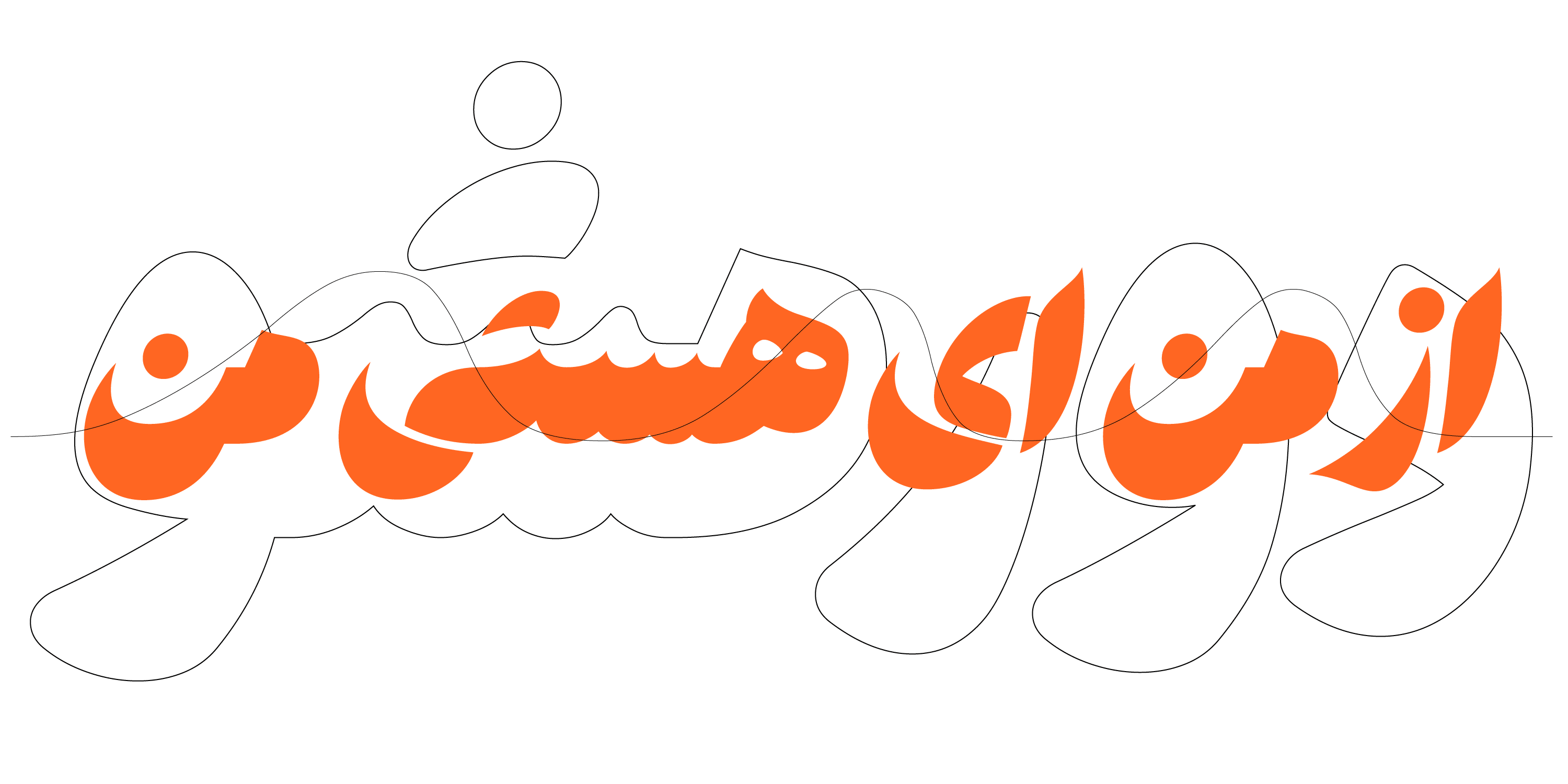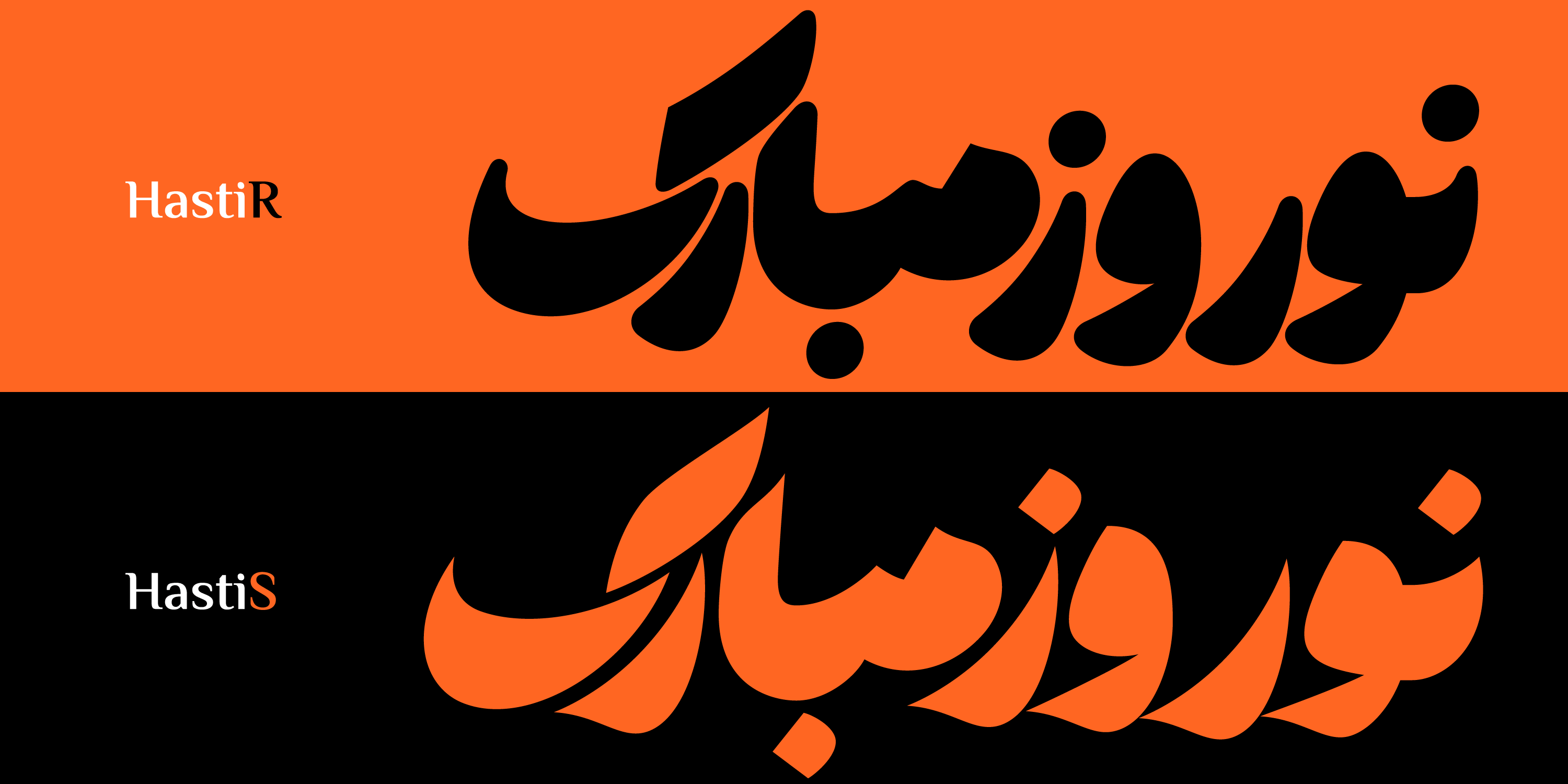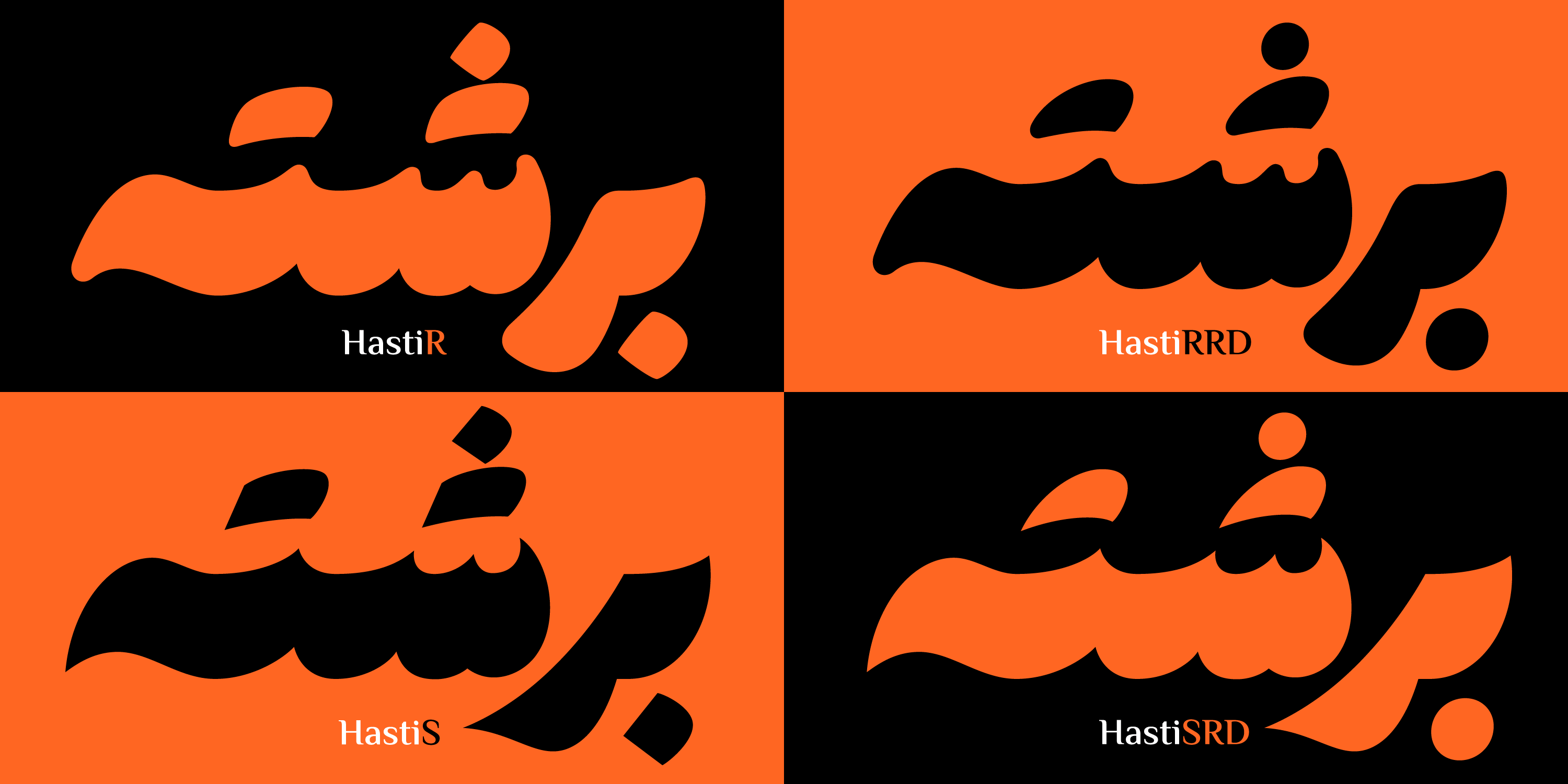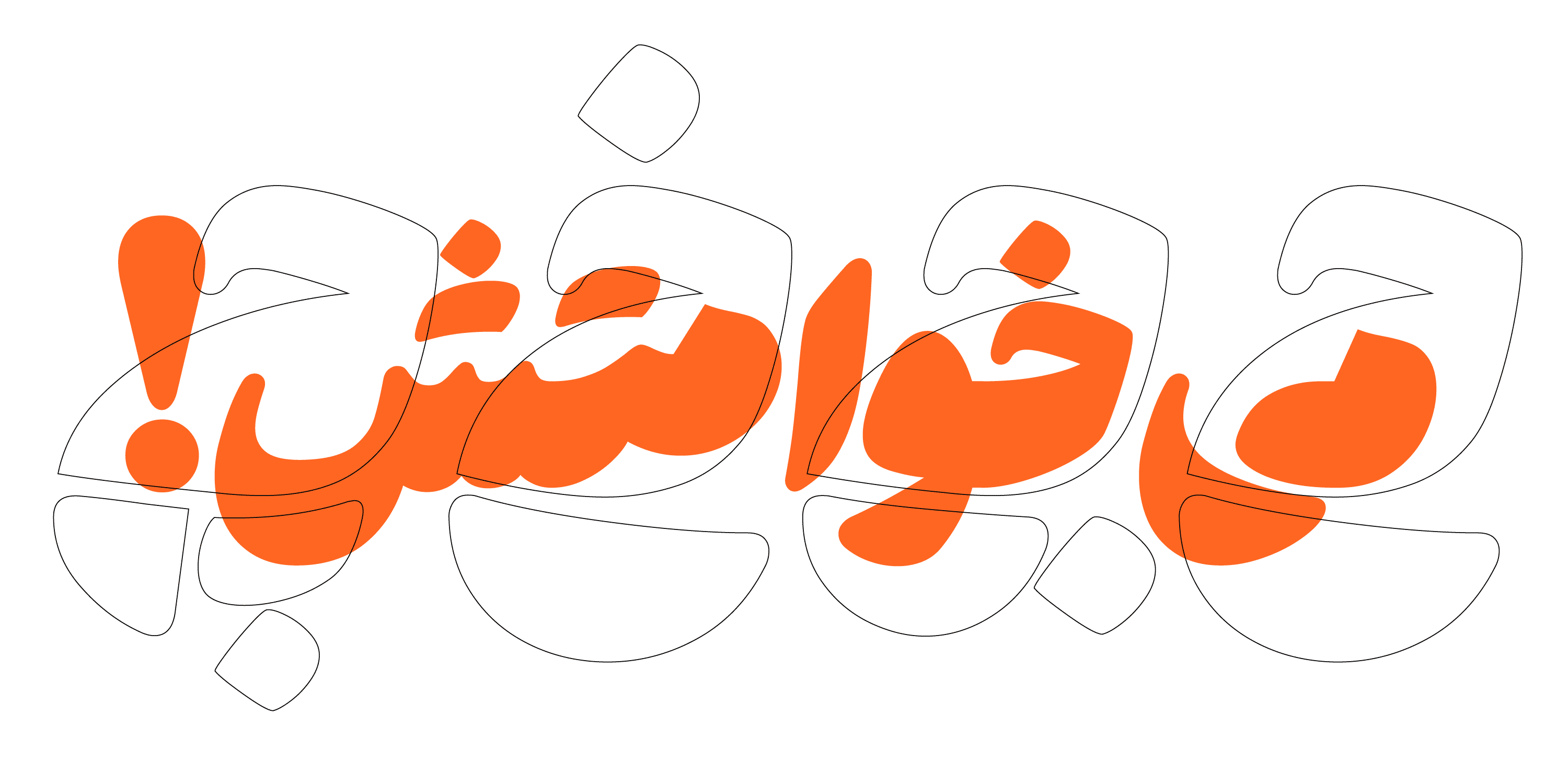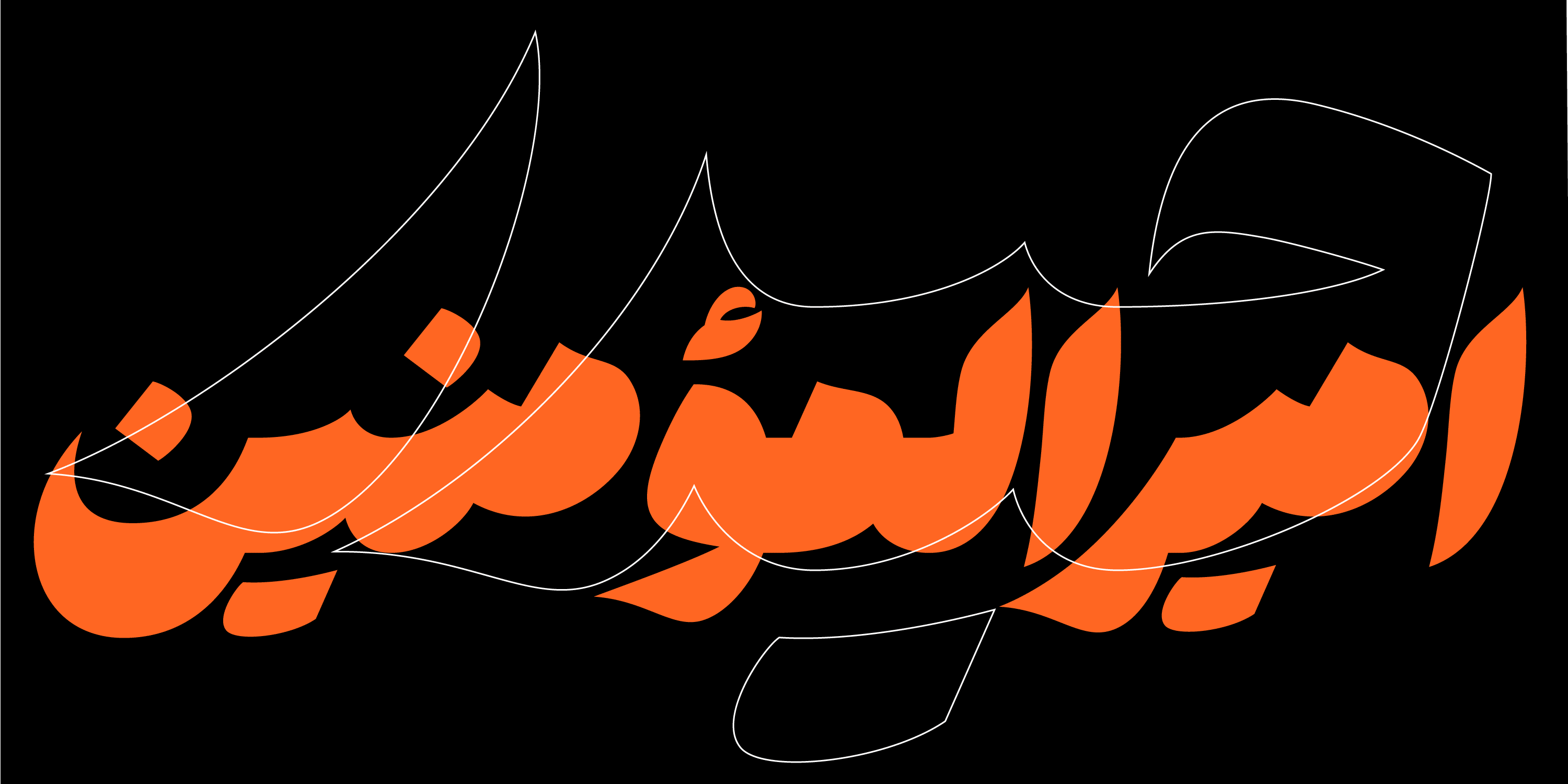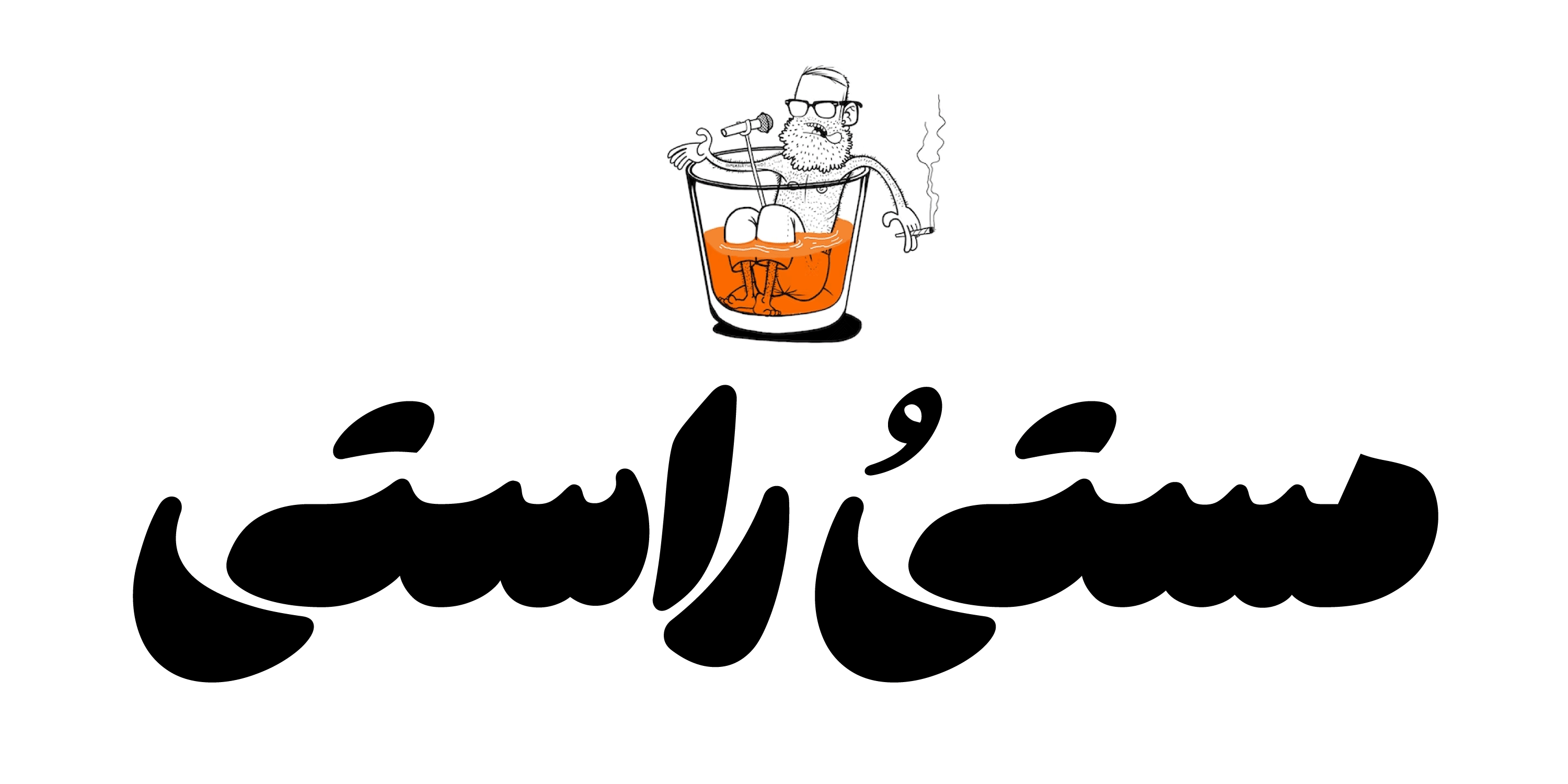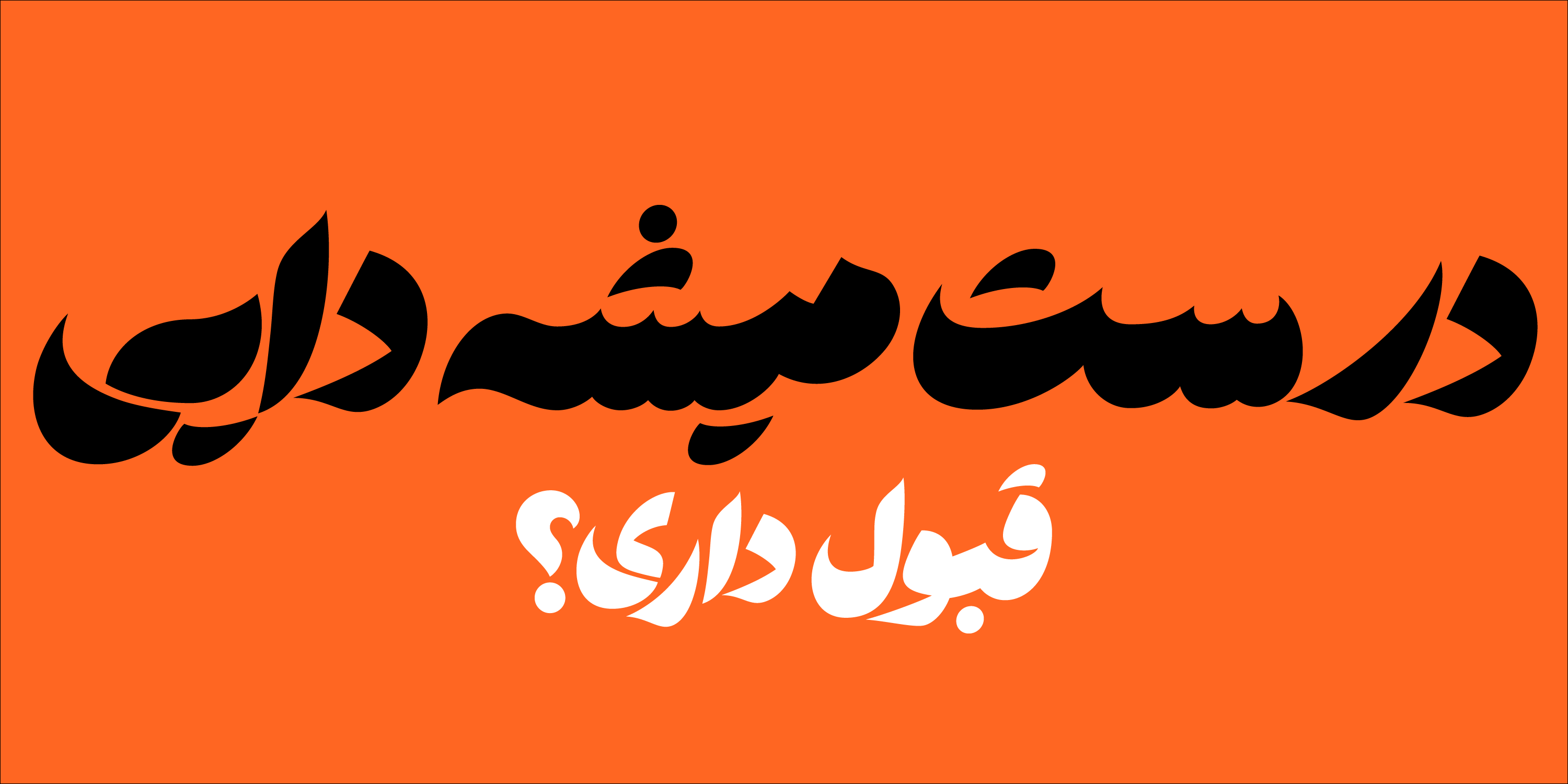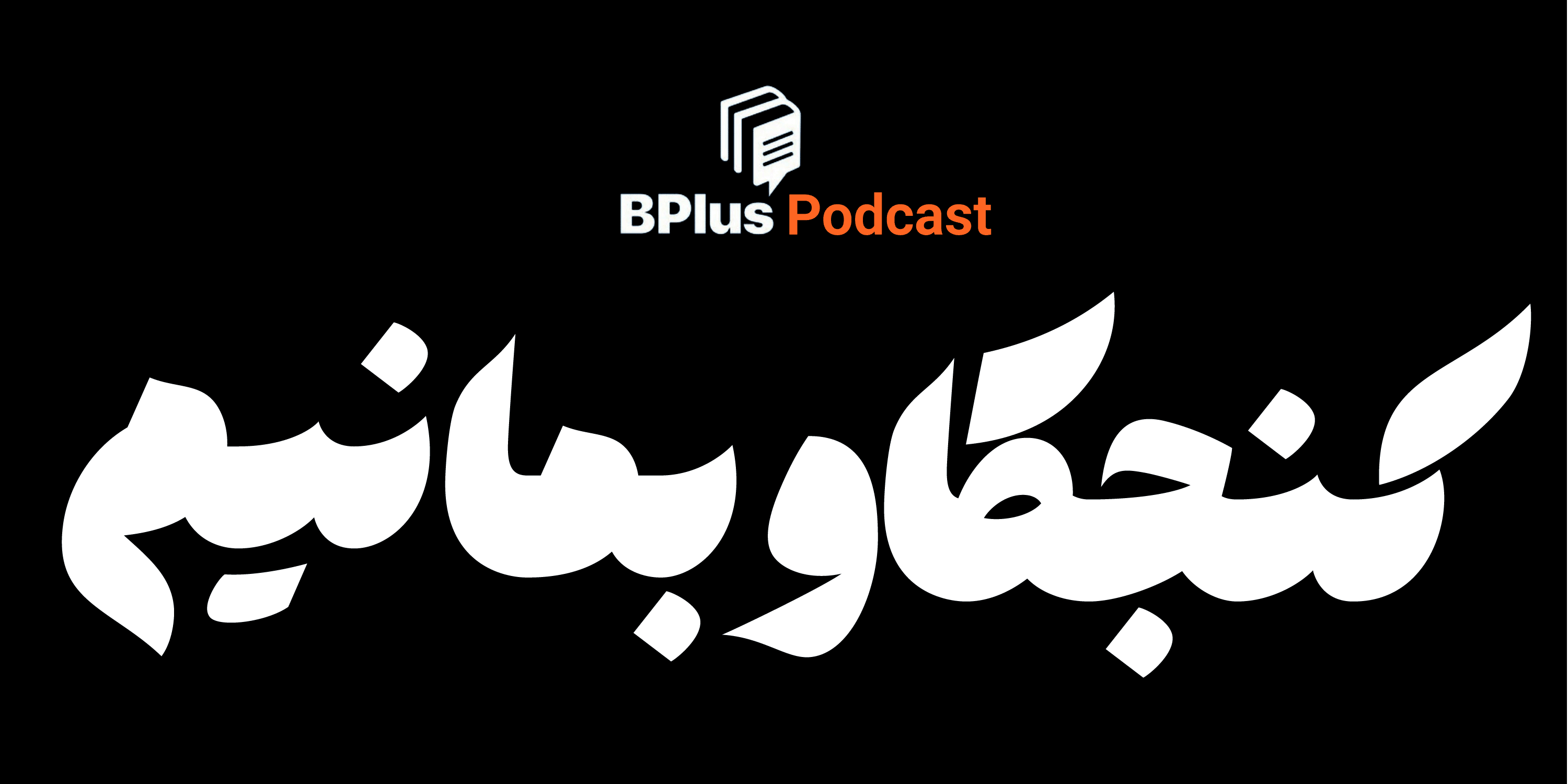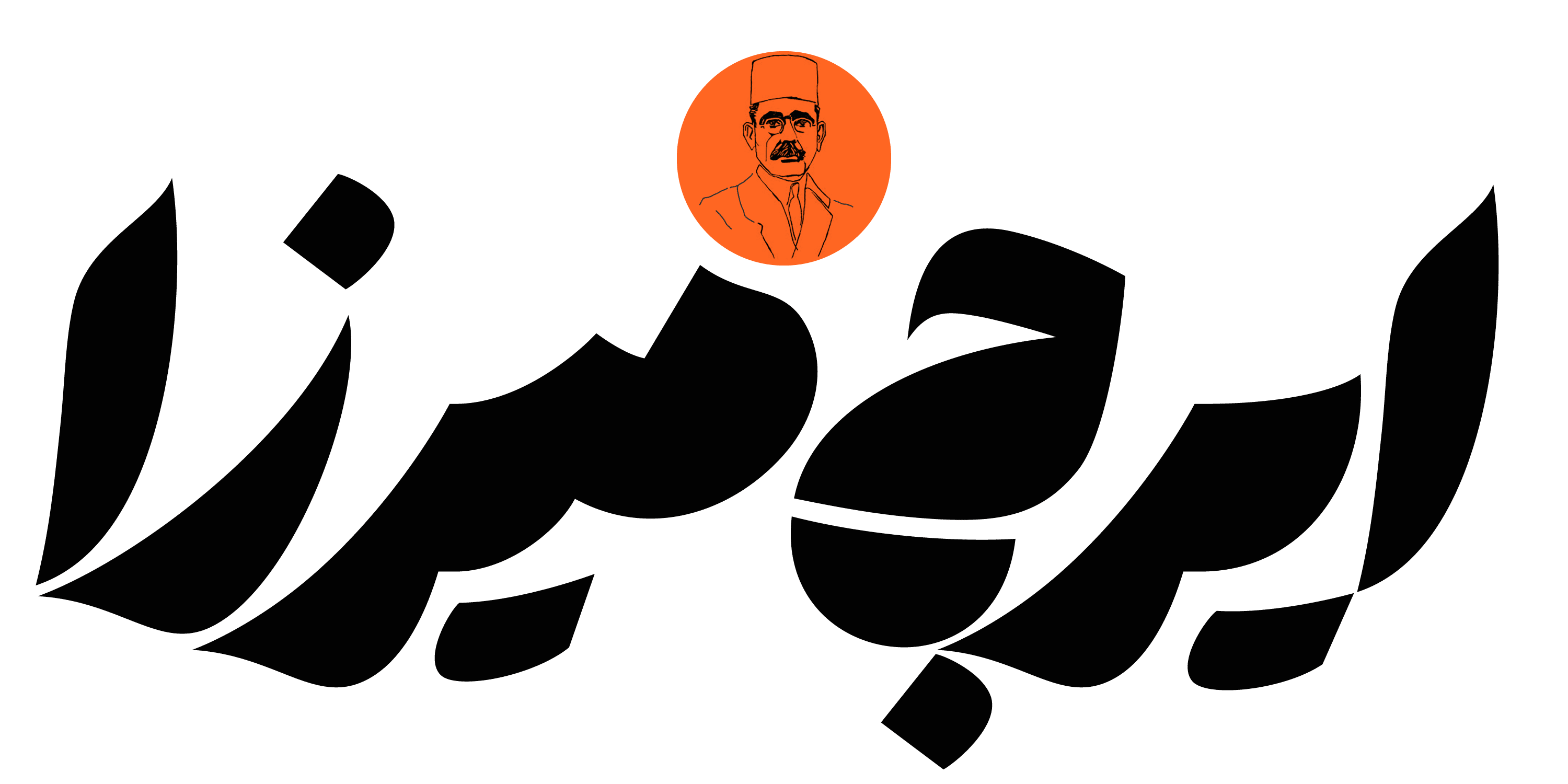
طی نیم قرن گذشته با ظهور دستگاه چاپ و کامپیوتر، خط فارسی کاملا پیرو خط نسخ بوده است اما نستعلیق هنوز برای ما دوست داشتنی و آشناست. هنوز شعر فارسی را جز با نستعلیق نمیتوانیم بپذیریم و اگر بخواهیم حس و حال ایرانی را در نوشتهای نشان دهیم نستعلیق را انتخاب میکنیم. فونت هستی انعکاسی از این حس آشنا و دوست داشتنی، در قالب یک فونت معاصر است.
فونت هستی متاثر از نستعلیقِ بازاری است. دیوار نویسیها و تبلیغات شهری که با قلمهای درشت خطاطی میشوند، ظرافت نستعلیق هنری را ندارد این حروف معمولاً بولدتر و فشردهتر نوشته میشود. فونت هستی تحت تاثیر این نوع حروف، حجیم و فشرده طراحی شده است.
در فونت هستی اثری از ترکیبات و اتصالات نستعلیق نیست اما شکل حروف تا حد امکان شبیه نستعلیق است.
برای فشردگی بیشتر، فرم حروف "ک ی ح" شکسته و منقطع شده است.
نسخه جدید فونت هستی دارای دو سبک گرد Rounded و تیز Sharp است.
هرکدام از دو سبک گرد و تیز با دو سبک نقطه در بسته وجود دارد. (نقطه کلاسیک و نقطه گرد)
فونت هستی در سیزدهمین رقابت جهانی گرانشان (۲۰۲۴) در بخش فونتهای عربی جایزه دوم را کسب کرد. (داوران این دوره با سختگیری جایزه نخست را به هیچ اثری اهدا نکردند.)
جایگزینهای خودکار
در هستی با توجه به حرف قبل یا بعد حروف کشیدهتر میشوند یا جای نقطهها عوض میشود.
جایگزینهای اختیاری
تعداد کمی حروف جایگزین در فونت هستی وجود دارد که طبق راهنمای درون بسته میتوانید آنها را تایپ کنید.
زبانها در فونت هستی
علاوه بر فارسی میتوانید عربی و دیگر زیر مجموعهها مانند کوردی و اردو را نیز با فونت هستی تایپ کنید. برای حروف انگلیسی از فونت Shrikhand استفاده شده است.
فونت هستی در کاربرد
فونت هستی میتواند در هرنوع تبلیغات و نوشته نمایشی استفاده شود. میتوان با آن پست اینستاگرام یا بنر سایت طراحی کرد، میتواند در تبلیغات شهری و بسته بندی استفاده شود و یا حتی تیتر یک روزنامه رسمی باشد. این به توانایی و جسارت شما بستگی دارد!
در نسخههای بعدی خواهید دید!
فونت هستی در نسخه اول خود، تا حد امکان ساده طراحی شده و فاقد ترکیبات است. دلیل سادگی این است که تمرکز بر دستیابی به شخصیت کلی تایپ باشد و پیش از هر توسعه تا حد امکان شکل حروف اصلاح شود. در مراحل بعد در قالب بهروز رسانی، امکانات کم کم به فونت هستی اضافه خواهد شد.
ترکیبات در هستی (بهزودی)
در نسخههای بعدی با اضافه شدن ترکیبات، شباهت فونت هستی به نستعلیق بیشتر خواهد شد.
هستی وریبل (بهزودی)
میزان گردی یا تیزی زاویهها میتواند در قالب یک وریبل فونت توسط شما تنظیم شود.